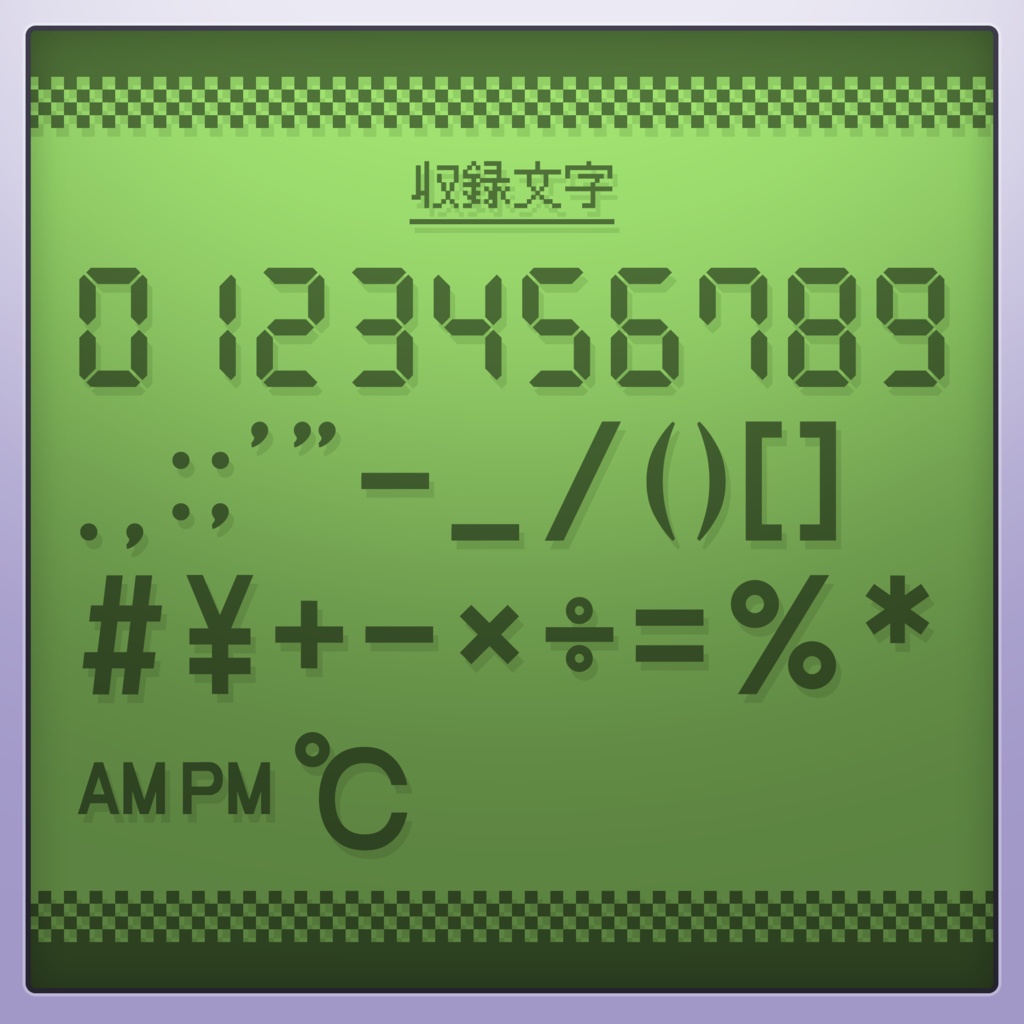
7セグ(デジタル数字)のバリアブルフォント/7SEGVF
7SEGVFは7セグ(デジタル数字)のバリアブルフォントです。 近未来風、デジタル時計等さまざまなコンテンツにマッチします! ウェイトとイタリックの二軸が可変なのでデザインのテイストに合わせてご使用ください。 数字、約物、記号を収録しております。 (アルファベットは未収録です。アイキャッチの収録文字をご覧ください) 気に入っていただけたらスキ!を押していただけると嬉しいです。 励みになります!